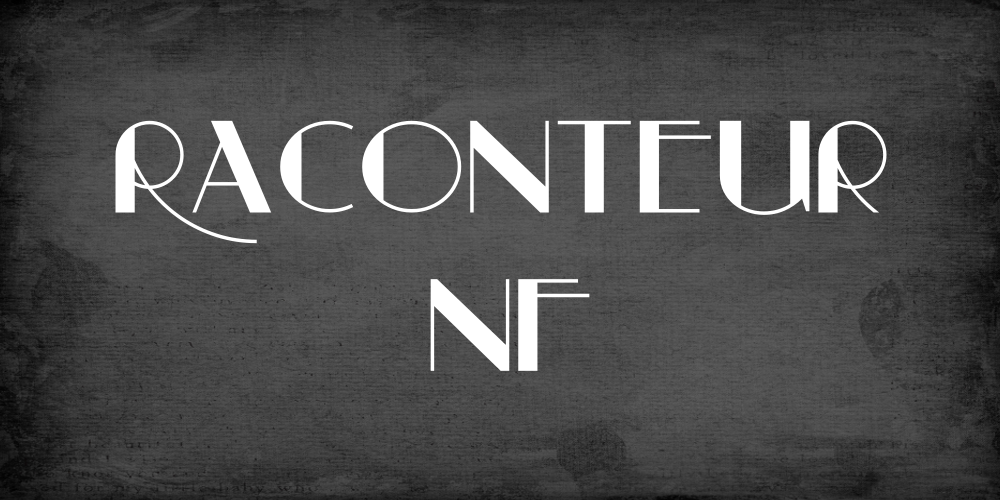
A ‘Raconteur NF’ é uma elegante fonte sans-serif que oferece um equilíbrio perfeito entre modernidade e sofisticação. Com a tipografia deste designer talentoso, Hamilton, a fonte traz uma textura suave e um estilo minimalista, ideal para criar designs profissionais sem perder o toque contemporâneo. Perfeita tanto para aplicativos de escrita pessoal quanto para design gráfico empresarial, ‘Raconteur NF’ é adequada para uso em variados formatos, desde websites até logotipos. Suas linhas leves e sua tipografia sóbria permitem que a informação seja facilmente legível, tornando-a uma escolha versátil para qualquer situação de design. Como parte da categoria de fontes sans-serif, ‘Raconteur NF’ oferece o toque moderno que seu projeto precisa para se destacar na internet vibrante e diversificada atual. Esta fonte é perfeitamente adaptável a diferentes tamanhos de texto, tornando-a uma opção versátil tanto para aplicações digitais quanto impressas. Como parte da ‘NF’ Family da Hamilton, ela oferece um conjunto rico de variantes que permitem ajustar o estilo conforme necessário, proporcionando flexibilidade e personalização. Para designers e profissionais do design gráfico, a fonte ‘Raconteur NF’ é uma excelente adição à sua coleção de ferramentas. Com seu equilíbrio perfeito entre simplicidade e sofisticação, ela oferece um leque de opções para o seu próximo projeto.